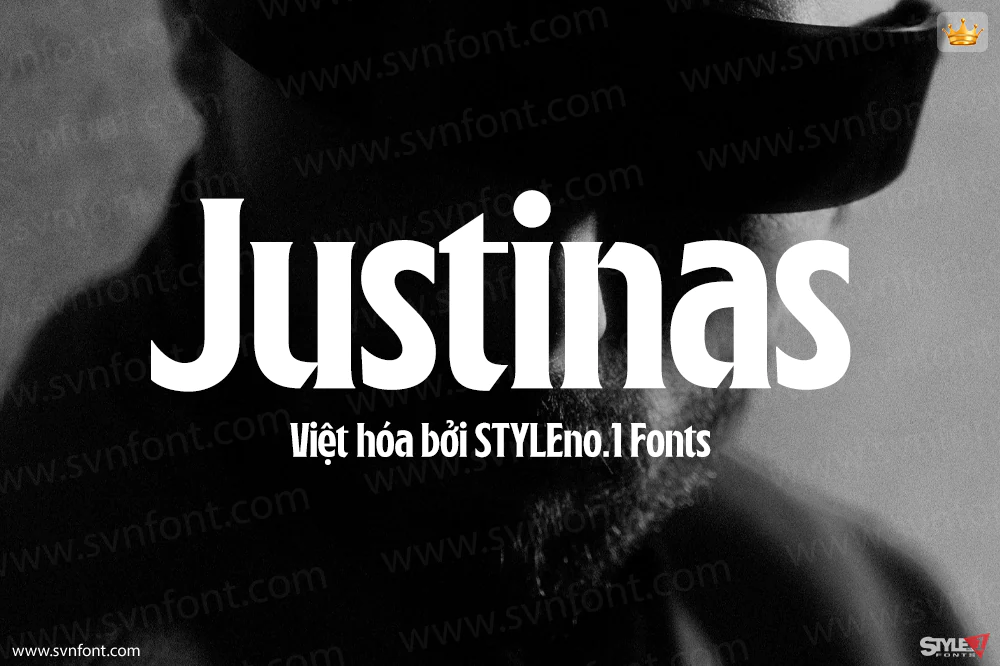
Justinas là một font serif display đậm, hoàn hảo cho các tiêu đề. Với thiết kế hẹp và các cạnh sắc nét, font mang đến sự thanh lịch và mạnh mẽ cho thiết kế của bạn.
Justinas kết hợp phong cách blackletter với nét cổ điển, tạo nên vẻ ngoài sang trọng phù hợp cho nhiều mục đích sử dụng. Font được trang bị các ký tự thay thế phong cách, cho phép bạn kết hợp linh hoạt để tạo thêm điểm nhấn và giúp thiết kế trở nên nổi bật!